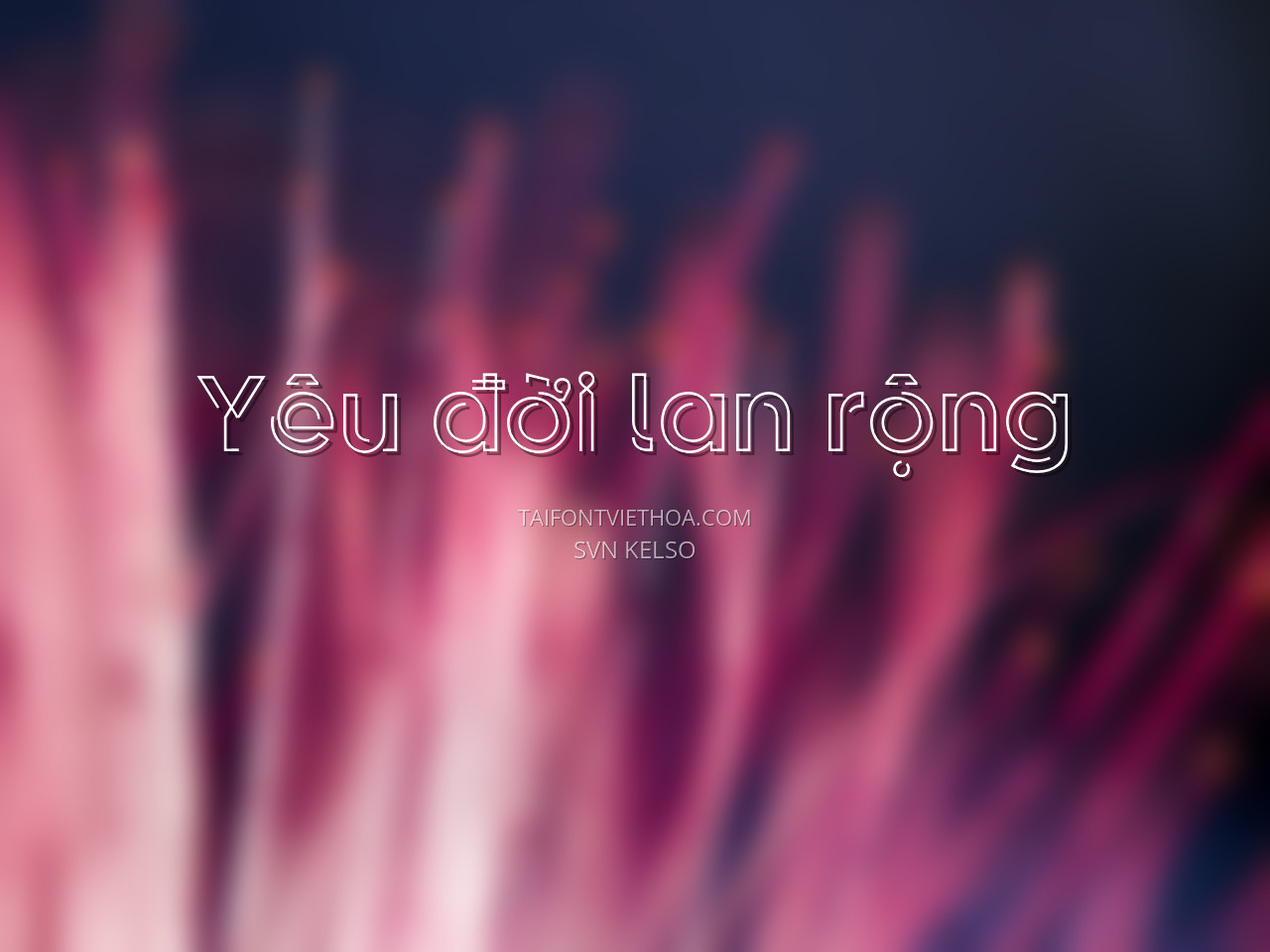
Font việt hóa SVN Kelso Medium
Tác giả Font: Adrian Talbot
Giới thiệu về font SVN Kelso Medium – Kiểu chữ sans-serif hiện đại, trung tính và dễ đọc
SVN Kelso Medium là phiên bản Việt hóa của font Kelso Medium – một kiểu chữ sans-serif mang phong cách hiện đại, trung tính với thiết kế cân đối và dễ đọc. Font phù hợp cho các dự án thiết kế thương hiệu, giao diện người dùng và truyền thông kỹ thuật số, mang lại cảm giác chuyên nghiệp và linh hoạt trong mọi kích thước.
Phiên bản Việt hóa của SVN Kelso Medium đã được Taifontviethoa.comchỉnh sửa kỹ lưỡng, hỗ trợ đầy đủ dấu tiếng Việt cùng hơn 70 ngôn ngữ khác. Font giúp nhà thiết kế dễ dàng áp dụng trong nhiều loại sản phẩm đa dạng mà vẫn giữ được phong cách hiện đại, tinh tế và dễ tiếp cận.
Thiết kế sans-serif cân đối – Ứng dụng đa dạng trong thương hiệu và giao diện
SVN Kelso Medium sở hữu cấu trúc sans-serif với các nét chữ mảnh vừa phải, cân đối và bo tròn nhẹ nhàng, tạo cảm giác thân thiện và dễ đọc. Font phù hợp cho tiêu đề, đoạn văn bản cũng như các thiết kế UI/UX, website, brochure và tài liệu quảng cáo. Phong cách trung tính và hiện đại của Kelso Medium rất thích hợp với các dự án đòi hỏi sự chuyên nghiệp và linh hoạt.